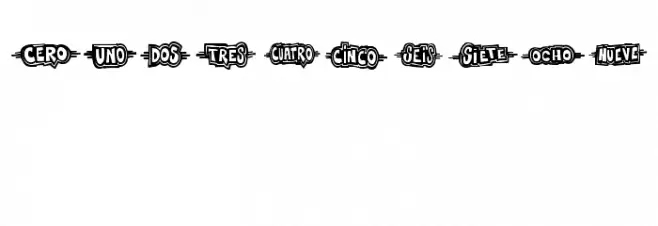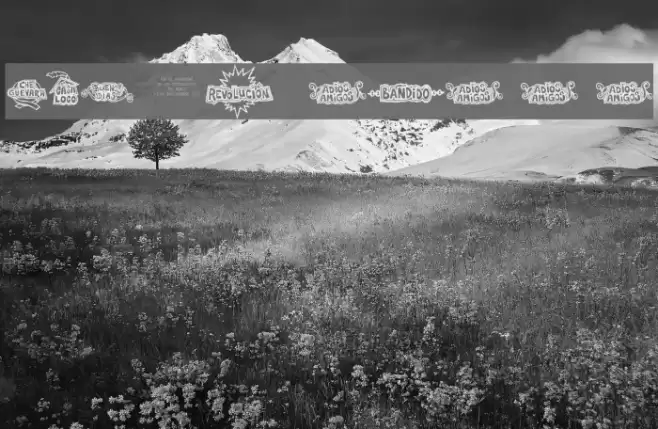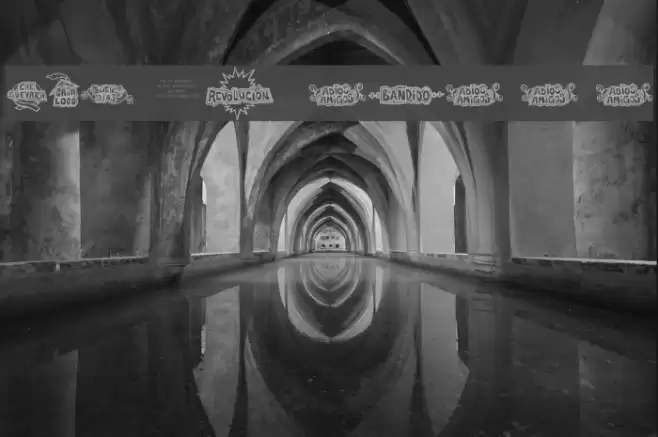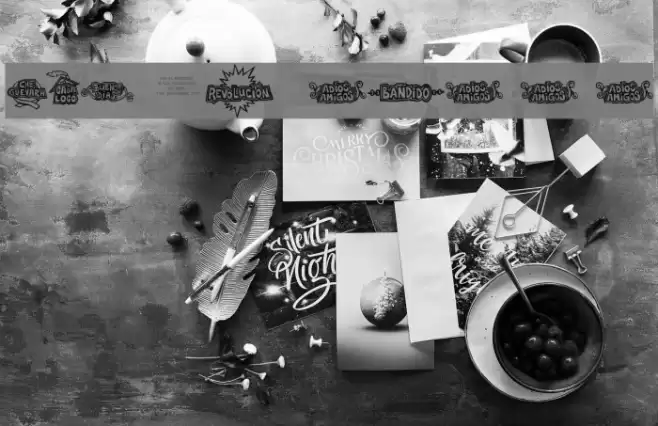
FE-CheVivaBanana Font
| Caz de utilizare | Headlines, Posters, Logos |
| Proiecte propuse | Ideal for event posters, themed merchandise, comic books, and playful branding. |
FE-CheVivaBanana